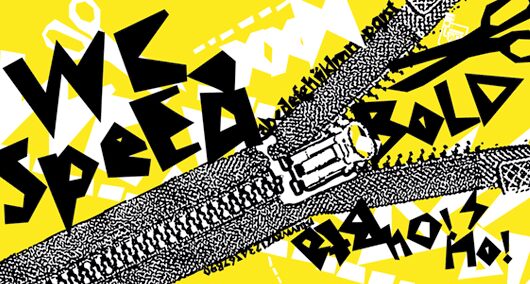
WC Speed, darmowy krój pisma typu display od WC Fonts, stawia na kanciasty, „wycinankowy” styl i surowy, poszarpany wygląd. Litery sprawiają wrażenie wykutych z ostrych odłamków – skosy, nagłe szpice i nierówne krawędzie nadają krojowi szybki, nerwowy rytm, daleki od nudnej, geometrycznej harmonii.
To naturalny wybór na ulotki deskorolkowe, plakaty muzyczne, horrory, tytuły gier czy wyraziste okładki, wszędzie tam, gdzie darmowy font ma przekazywać surową energię, a nie gładki szlif. Świetnie sprawdza się też w krótkich logotypach czy monogramach, bo połamane, przypominające nacięcia nożem sylwetki zachowują swój charakter nawet w krótkich słowach.